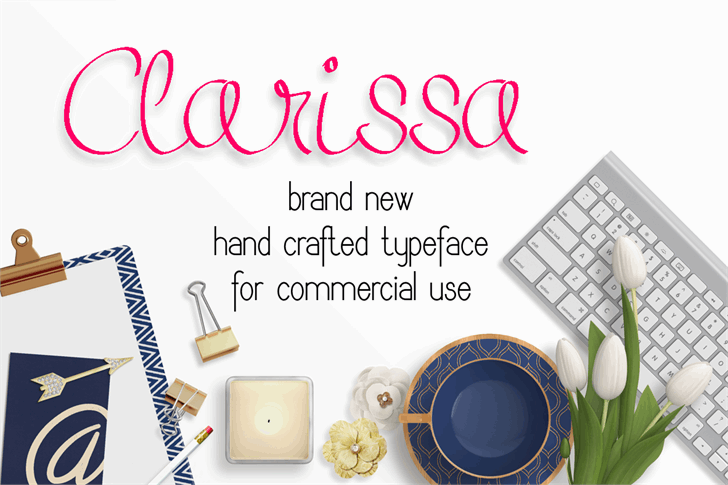
A fonte Clarissa é uma nova e elaborada face à mão, desenvolvida pela designer Eva Barabasne Olasz. Inspirada na caligrafia artística e moderna, a fonte é perfeita para múltiplas aplicações, desde identidades visuais de empresas até trabalhos de design gráfico. Com uma gama completa de caracteres incluindo letras maiúsculas, minúsculas, números e sinais especiais (veja todos os caracteres completos no segundo quadro), Clarissa oferece flexibilidade para criar designs com um toque único e sofisticado. Suas linhas sutis e detalhes aprimorados garantem uma experiência de leitura confortável que vai além das aplicações tradicionais, tornando-a uma opção versátil e elegante no seu portfólio de fontes.
Designer: Eva Barabasne Olasz